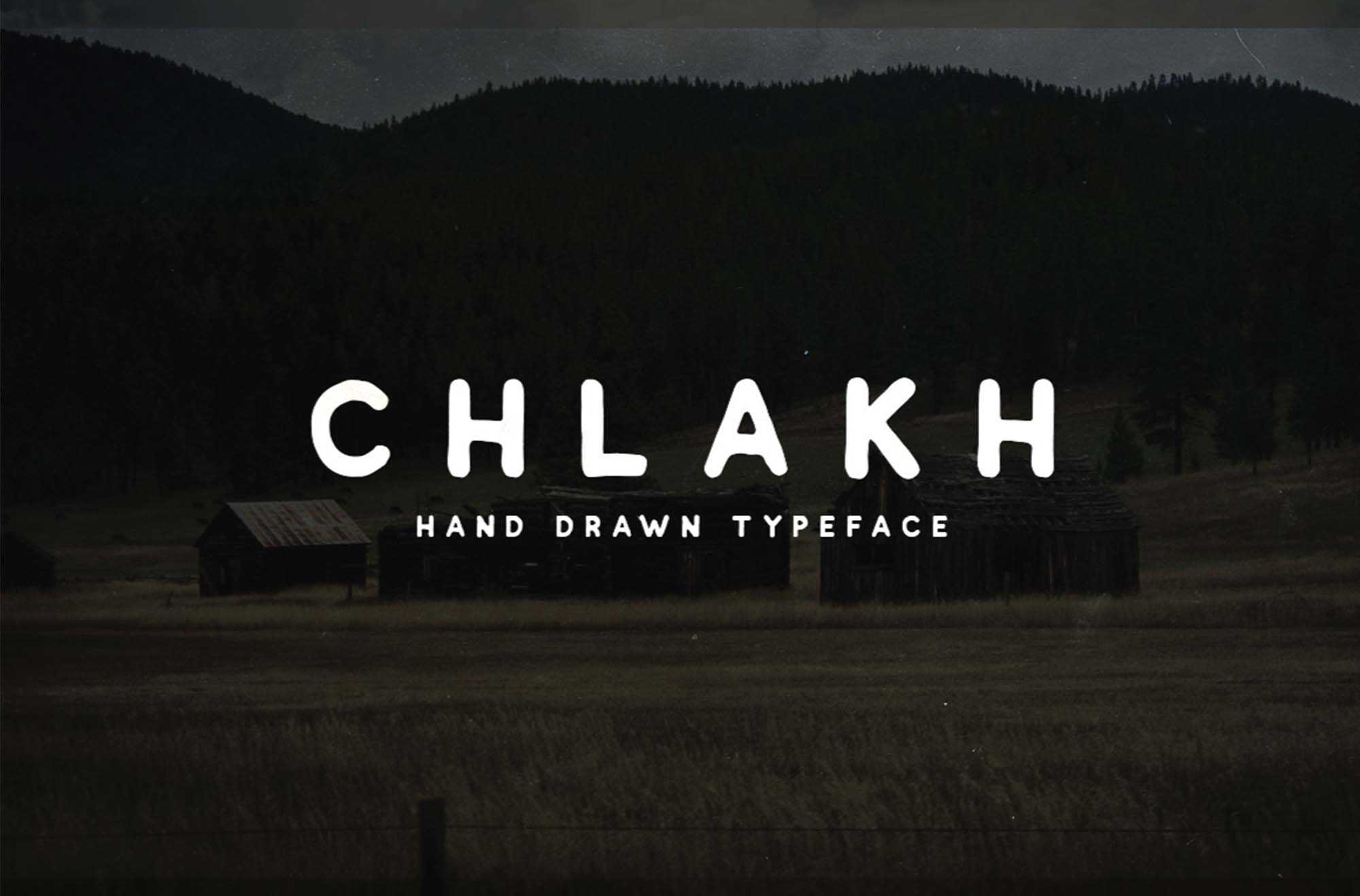
Chlakh Free Font
A fonte Chlakh Free Font surge em um cenário design contemporâneo que valoriza tanto a simplicidade quanto o vintage. O movimento minimalista e a renovação da cena vintage não são apenas tendências, mas têm se tornado uma grande transformação na indústria de design. Esta fonte minimalista é perfeita para estilos modernos de design gráfico, mas também se adapta perfeitamente a ambientes nostálgicos, como restaurantes e lojas de conveniência. Chlakh, uma das muitas opções de fontes gratuitas disponíveis, traz consigo um toque de nostalgia, ideal para ambientes que buscam criar um clima de conforto e familiaridade. Esta fonte é uma ótima escolha para quem trabalha no ramo de restaurantes, desde o desenvolvimento de menus até a criação de itens promocionais, como camisetas, onde ela transmite um espírito de velhos restaurantes e de ambientes retro. Chlakh é perfeitamente adaptada para criar atmosferas nostálgicas e simpáticas, atraindo clientes que valorizam essa atmosfera única e agradável.